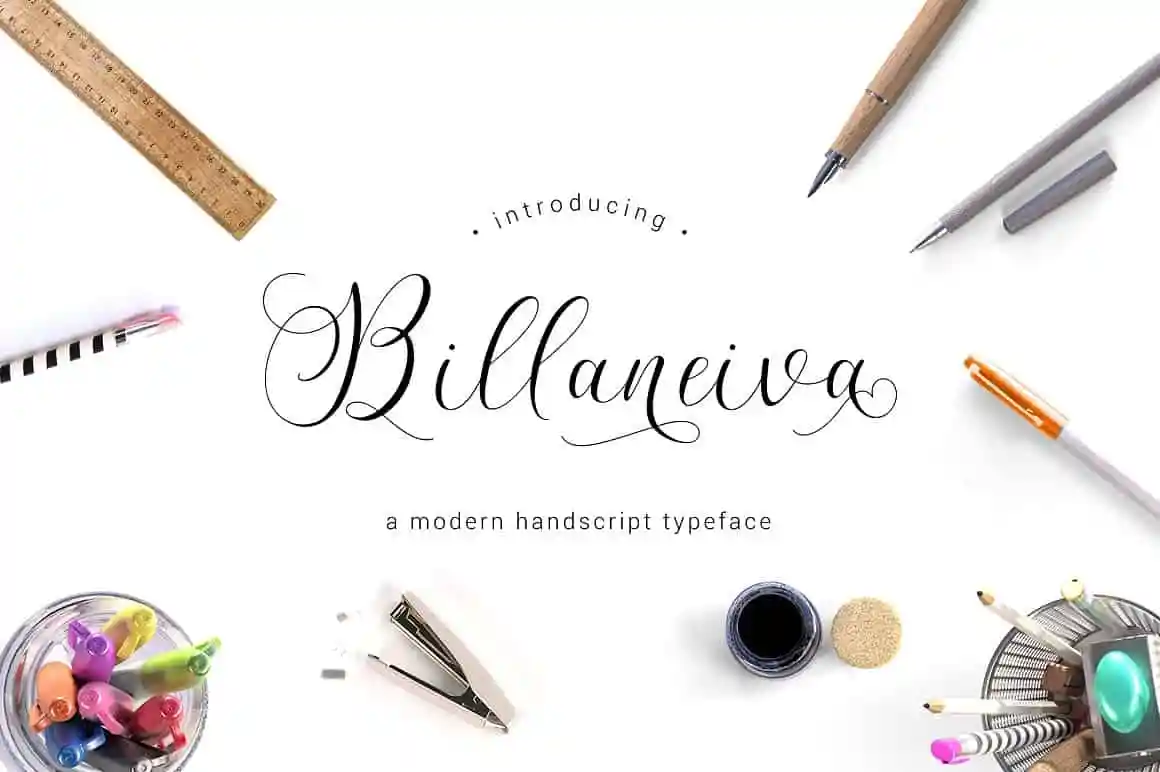
Billaneiva Script Font
A fonte Billaneiva Script é perfeita para quem busca uma aparição sofisticada e chic sem abrir mão do charme natural das fontes script. Esta moderna tipografia de hand-lettering oferece um toque realista de humanidade, com detalhes cuidadosamente criados que o tornam único entre as opções disponíveis no mercado. Ideal para criações de moda, sites e lojas online focadas em tendências, boutique de casamentos ou qualquer negócio que deseja destacar-se com elegância, Billaneiva é uma escolha inteligente para quem busca um toque personalizado e artesanal. Tudo o que você precisa fazer é digitar suas palavras e já verá os maravilhosos resultados que a fonte produz. Billaneiva é perfeito tanto para profissionais da moda quanto para blogueiros de estilo, criando mensagens vibrantes e intrigantes em uma variedade de ambientes digitais.